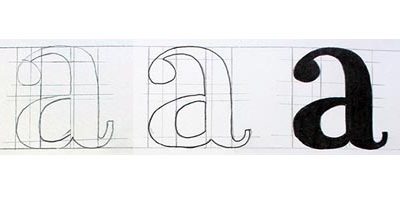
Ejercicios de lettering
Cuando se empieza con los ejercicios para aprender lettering, es conveniente practicar antes un poco de caligrafía para conocer los trazos y las características de cada letra según la herramienta de escritura que utilicemos (pluma, pincel…) y el alfabeto (romano, gótico, Brush Script…). Esto hará que luego se obtengan mejores resultados en caligrafía.
Después, se pasa a hacer ejercicios de transición de caligrafía a lettering, es decir, de escribir letras a dibujar letras. En esta parte de ejercicios de lettering es fundamental aprender a dibujar cada letra por partes o por bloques para entender su estructura y su construcción.
Luego se paso ejercicios de lettering para escribir varios tipos de alfabeto o abecedarios. Normalmente se empieza por las letras romanas modernas, luego las sin remate, con remate de bloque, latinas, script, gótica e interlock.
Más tarde, cuando conozcamos estos alfabetos, los ejercicios de lettering toman matiz de las variaciones de cada tipo de letra para hacerlos más personales, así como ejercicios de acabado.
Por último, se pasa hacer los ejercicios de lettering acerca de combinar estos alfabetos con composiciones que juegan con la forma, el tamaño, el acabado y el ritmo de cada palabra de la frase para conseguir esas obras de lettering tan bonitas que vemos.
En este apartado podéis encontrar ejercicios de lettering paso a paso con instrucciones y con vídeos para que aprendáis a dibujar cualquier tipo de letra y sus variaciones.